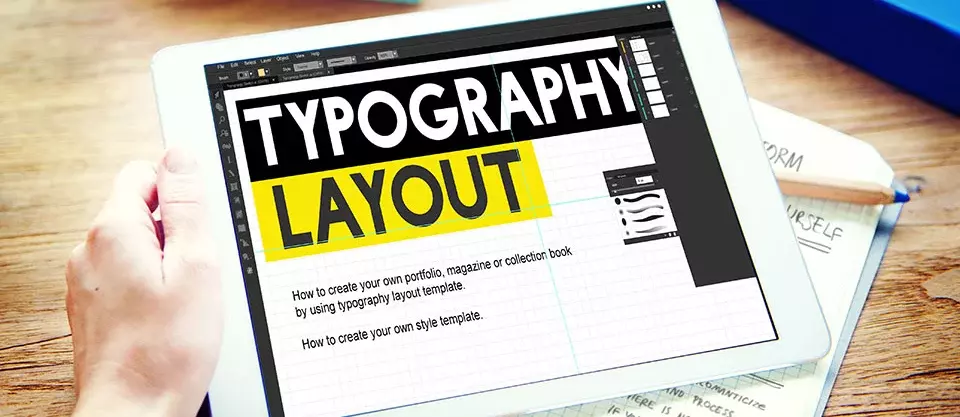
Fundamentos de la tipografía responsiva en el diseño web adaptativo
La correcta aplicación de las fuentes tipográficas desempeña un papel fundamental en el diseño web adaptativo. En este contexto, la tipografía responsiva influye de manera significativa en la percepción de una página web, asegurando que se adapte correctamente a diferentes dispositivos y tamaños de pantalla.
La importancia de la tipografía en el diseño web adaptativo
Originalmente, el término tipografía hacía referencia al oficio de imprimir textos con tipos móviles, las llamadas letras de imprenta. Históricamente, este concepto está estrechamente relacionado con el desarrollo de la escritura y su reproducción técnica mediante la imprenta. Hoy en día, el significado es mucho más amplio: la tipografía abarca el diseño de las letras y su aplicación en el ámbito digital, como en páginas web o programas informáticos.
Se distinguen dos áreas dentro de la tipografía:
- Microtipografía: configuración del tipo de letra como tal, así como de los espacios entre caracteres y palabras
- Macrotipografía: abarca todos los aspectos del diseño de una página de texto impresa o digital, incluyendo el formato de página, la caja de composición, el tamaño de la letra, el interlineado, el número y el ancho de las líneas, así como la disposición de otros elementos gráficos (por ejemplo, imágenes).
Tipografía en medios digitales e Internet
El diseño de las fuentes en documentos de texto digitales y en la web se conoce como tipografía web. Al igual que en la tipografía tradicional, la legibilidad en la web depende de factores como el tamaño de la letra, la longitud de las líneas y el interlineado. Además, en las fuentes web se deben considerar los formatos de archivo y la técnica de visualización de las fuentes.
El uso de diferentes tipos de letra en la web ha evolucionado considerablemente. En el pasado, la capacidad de mostrar tipografías en un navegador estaba claramente limitada: solo unas pocas, como Times New Roman o Arial, se consideraban universalmente compatibles, ya que estaban instaladas en la mayoría de los ordenadores y podían utilizarse en una página web. Hoy en día, se emplean tipografías mucho más diversas en forma de fuentes web. Las fuentes web son fuentes que el navegador carga desde la red mediante CSS junto con la página web que se va a mostrar.
Tanto las fuentes web como las fuentes instaladas localmente, las tipografías utilizadas hoy en día son casi exclusivamente fuentes vectoriales, que se mantienen nítidas y legibles sin importar el nivel de ampliación y se representan en el navegador mediante una matriz de píxeles. Los formatos más comunes para fuentes vectoriales son TrueType (TTF), OpenType (OTF) y Web Open Font Format (WOFF2).
Fuentes variables
Una evolución de las fuentes vectoriales y las fuentes web son las llamadas fuentes variables (variable fonts). Se trata de tipografías que reúnen varios estilos, como diferentes grosores de trazo (peso), anchuras, inclinaciones u otras propiedades tipográficas en un único archivo de fuente. A diferencia de las fuentes clásicas, en las que cada estilo debe cargarse como un archivo independiente, las fuentes variables pueden ajustarse de forma continua y flexible.
Esta técnica permite adaptar la tipografía de forma flexible a diferentes tamaños de pantalla, resoluciones o requisitos de diseño de la maquetación, sin tener que alternar entre variantes fijas de la fuente. Especialmente en el diseño web adaptativo, esto ofrece ventajas: los tamaños y grosores de la letra pueden escalarse de manera fluida, de modo que la familia tipográfica se integra de forma armoniosa en distintos encuadres. Al mismo tiempo, las páginas web se benefician de un número reducido de archivos de fuentes, lo que puede repercutir positivamente en los tiempos de carga y en el rendimiento.
¿Qué caracteriza a la tipografía en el diseño web adaptativo?
La tipografía web ya ha evolucionado enormemente, pero el diseño adaptativo o reactivo de las páginas de Internet plantea nuevos retos a las personas que se dedican al diseño web. El diseño web adaptativo es hoy una técnica muy extendida en la que la visualización del contenido de una página se ajusta al dispositivo utilizado y al tamaño de la pantalla. La adaptación de todos los contenidos a cada tamaño de pantalla afecta, por supuesto, a la tipografía, que también debe integrarse de forma coherente en el área visible.
En el mejor de los casos, el tamaño de la letra y los saltos de línea del texto se adaptan a cualquier área de visualización (viewport). Las funciones de CSS permiten además la llamada tipografía fluida, en la que los tamaños de la letra se ajustan de forma continua al tamaño del área de visualización. Con funciones como clamp() se pueden definir valores mínimos, ideales y máximos para el tamaño de la tipografía, de modo que los textos no se muestren ni demasiado pequeños ni excesivamente grandes.
Además de la adaptación de las fuentes vectoriales al tamaño de la pantalla y del área de visualización, las técnicas de maquetación subyacentes también evolucionan constantemente. Enfoques de CSS como las consultas de contenedores permiten alinear la tipografía y el diseño no solo con la pantalla completa, sino también con el tamaño de elementos individuales de la página. De este modo, los componentes pueden reaccionar de forma individual al espacio disponible, independientemente del área de visualización global. Esto permite ajustar la tipografía en diseños modulares de manera aún más precisa a distintos escenarios de uso.